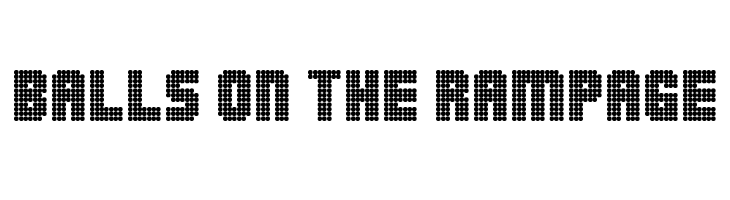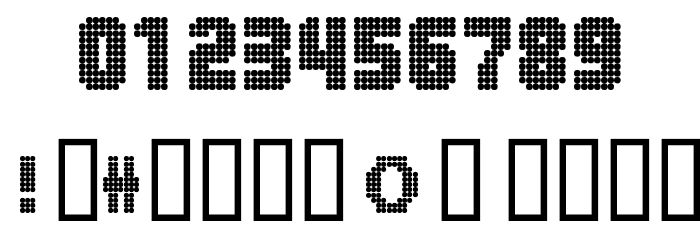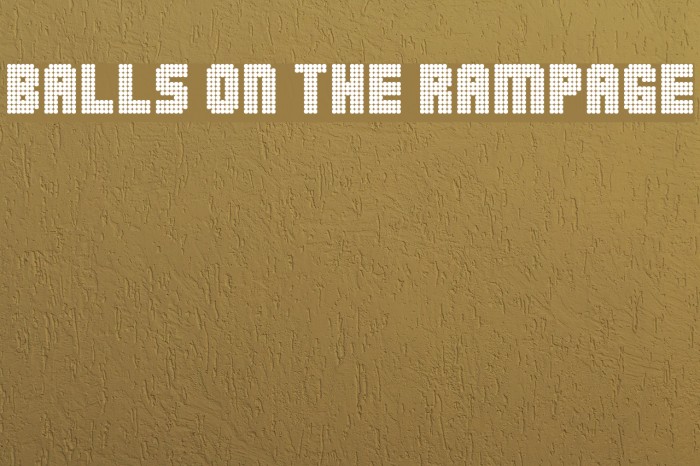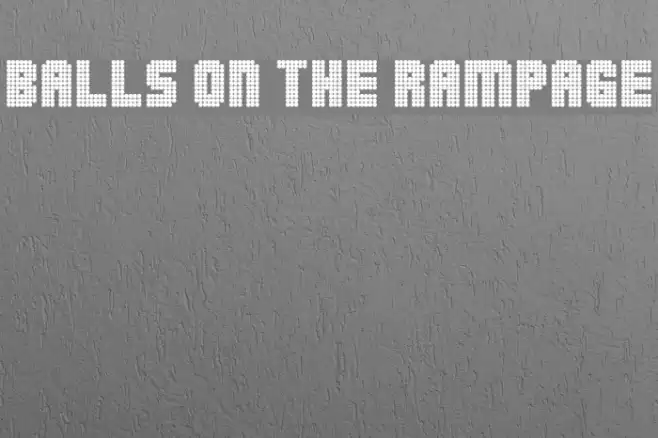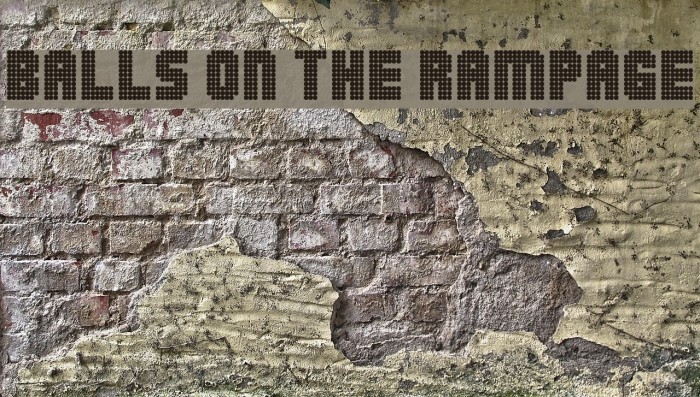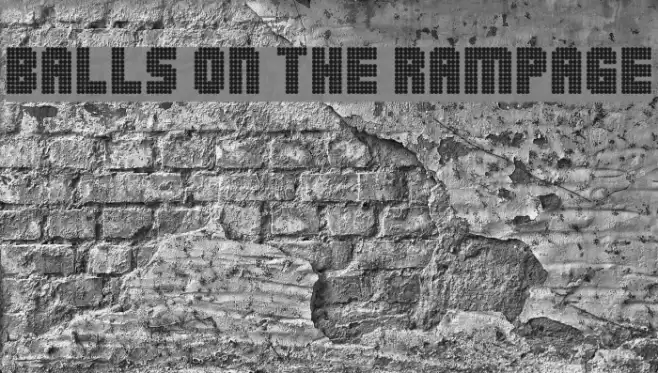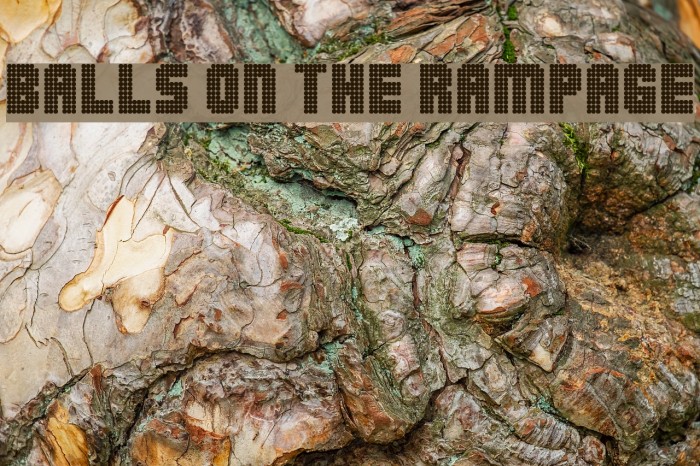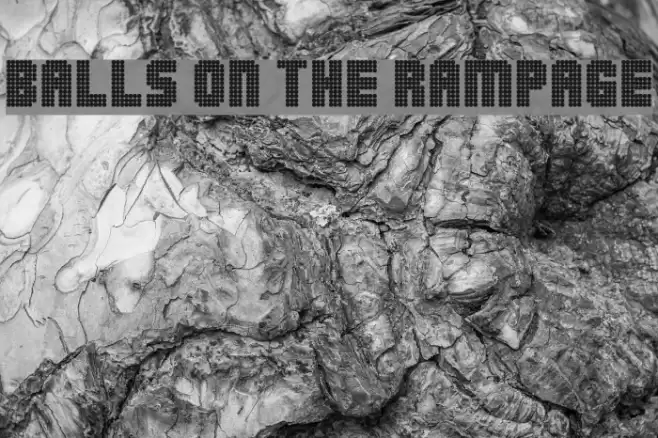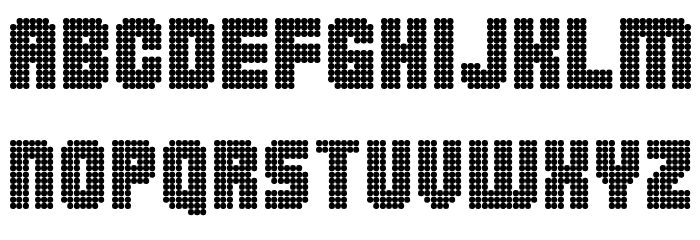
Balls on the rampage Font
Fonts by Jacob Fisher - www.pizzadude.dk
| Anwendungsfall | Headlines, Logos, Digital displays |
| Vorgeschlagene Projekte | Ideal for digital art, retro-themed designs, video game graphics, and tech-related branding. |